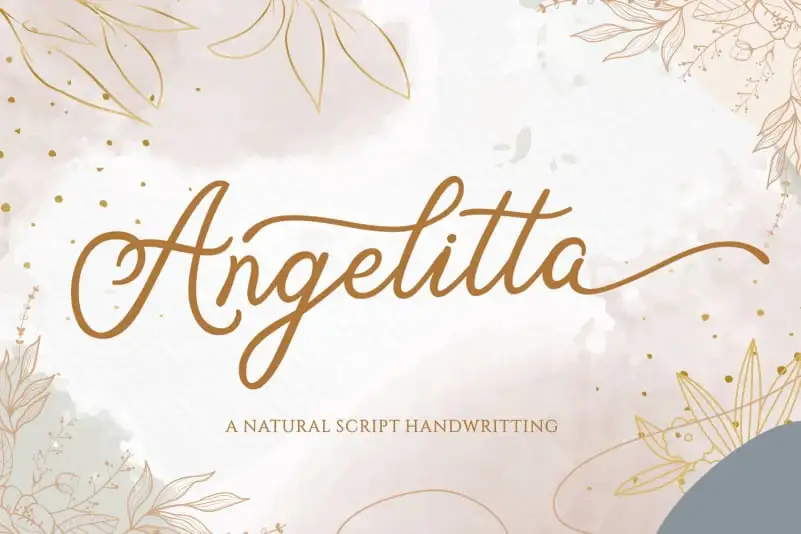
Angelitta Calligraphy Font – Download Grátis
A Angelitta Calligraphy Font é uma escolha perfeita para quem busca elegância e charme em cada projeto de design. Sua aparência sofisticada e delicada torna-a ideal para eventos como convites de casamento, cartões de agradecimento, cartazes de citações e até mesmo logomarcas e cards de negócios. A sua beleza não tem limite e pode ser encontrada em qualquer projeto que precise de uma mão-doida única e elegante. Ideal para qualquer designer gráfico que deseja dar um toque especial a seus trabalhos, seja ele no campo da decoração ou na publicidade, a Angelitta Calligraphy Font está aqui para ajudá-lo a criar algo realmente único e memorável.